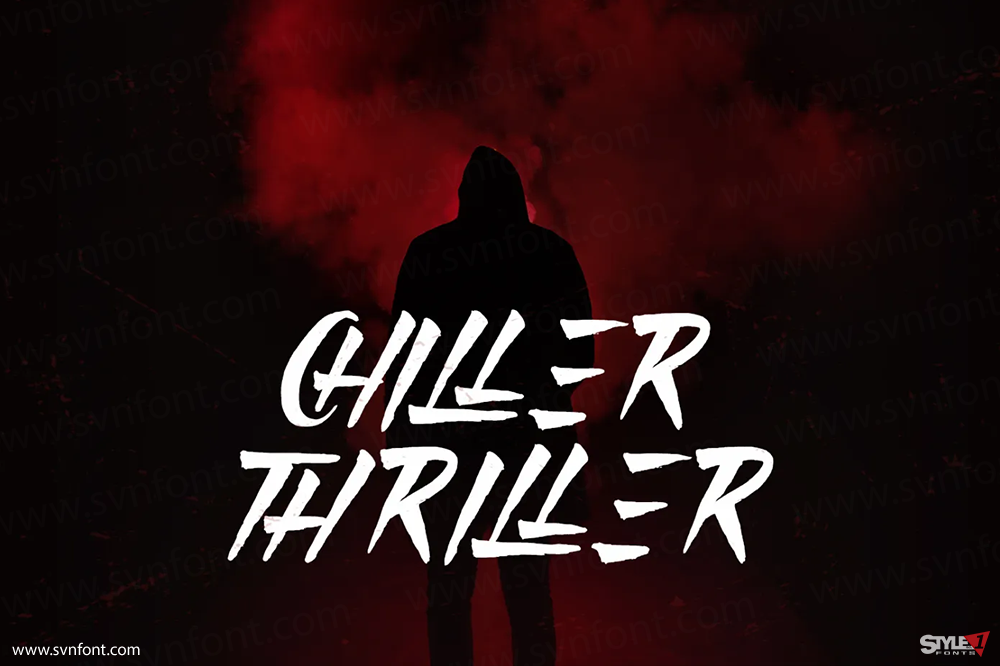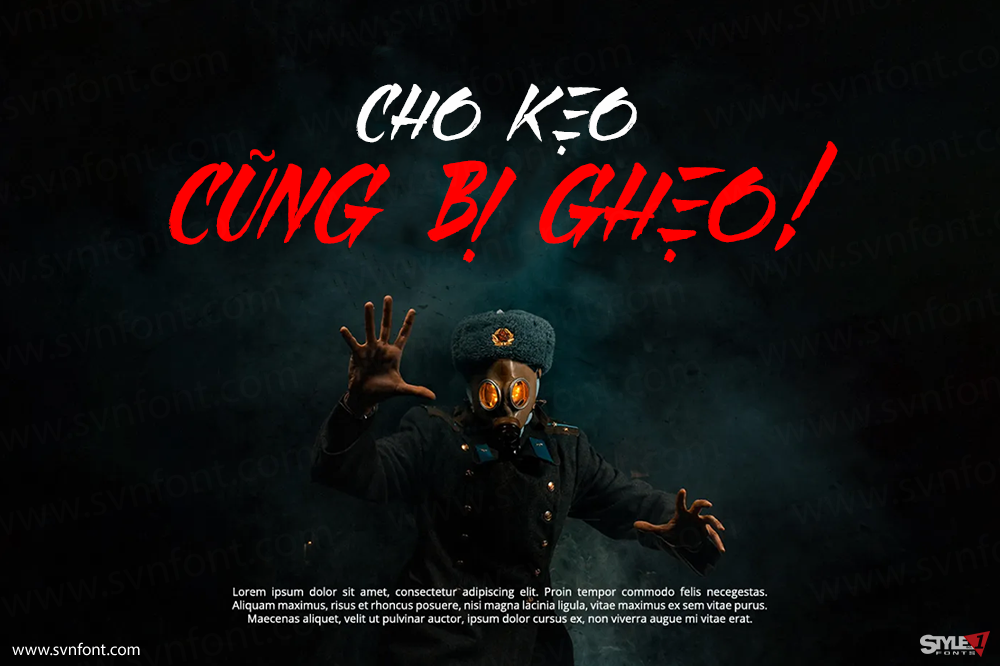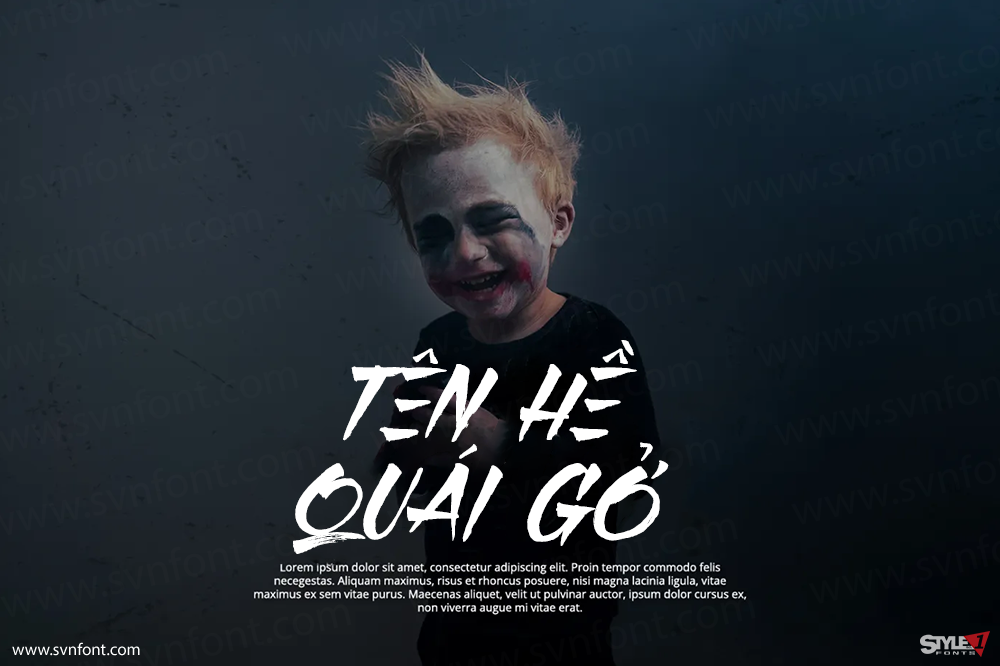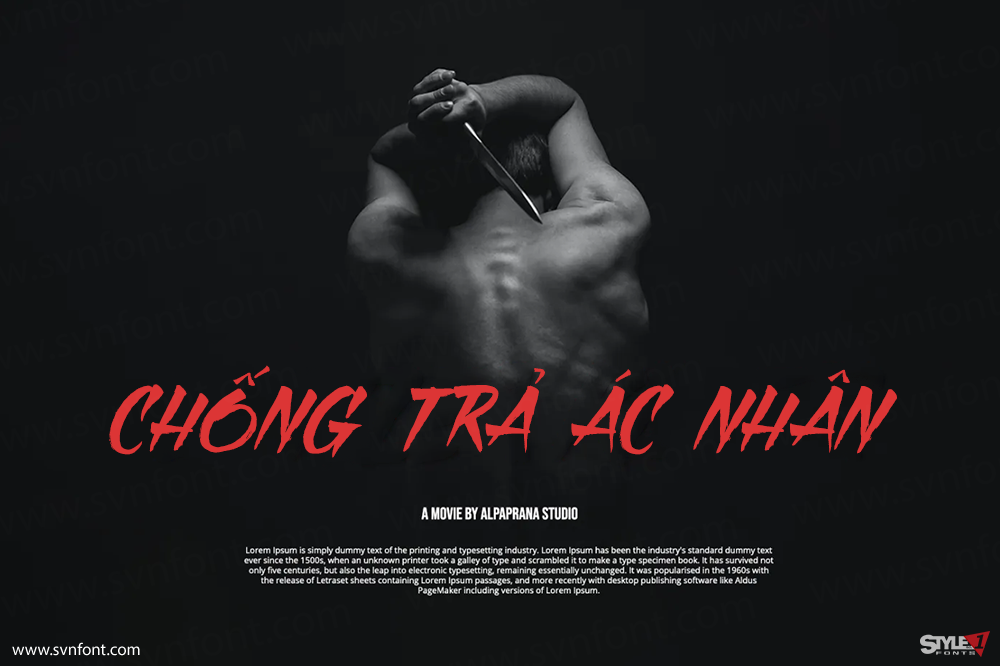
Black Pumpkin là một font hiển thị kinh dị tuyệt đẹp với cảm giác dễ thương và vui tươi. Nó sẽ được sử dụng hoàn hảo cho việc xây dựng thương hiệu, thiết kế logo, chữ viết tay, logotype, quần áo, áp phích, tạp chí, bao bì, túi mua sắm, áo thun, bìa sách, nhiếp ảnh, các sự kiện đặc biệt và các dự án thiết kế khác.
Nhà thiết kế: Alpaprana Studio
Nhà phát hành: Alpaprana Studio